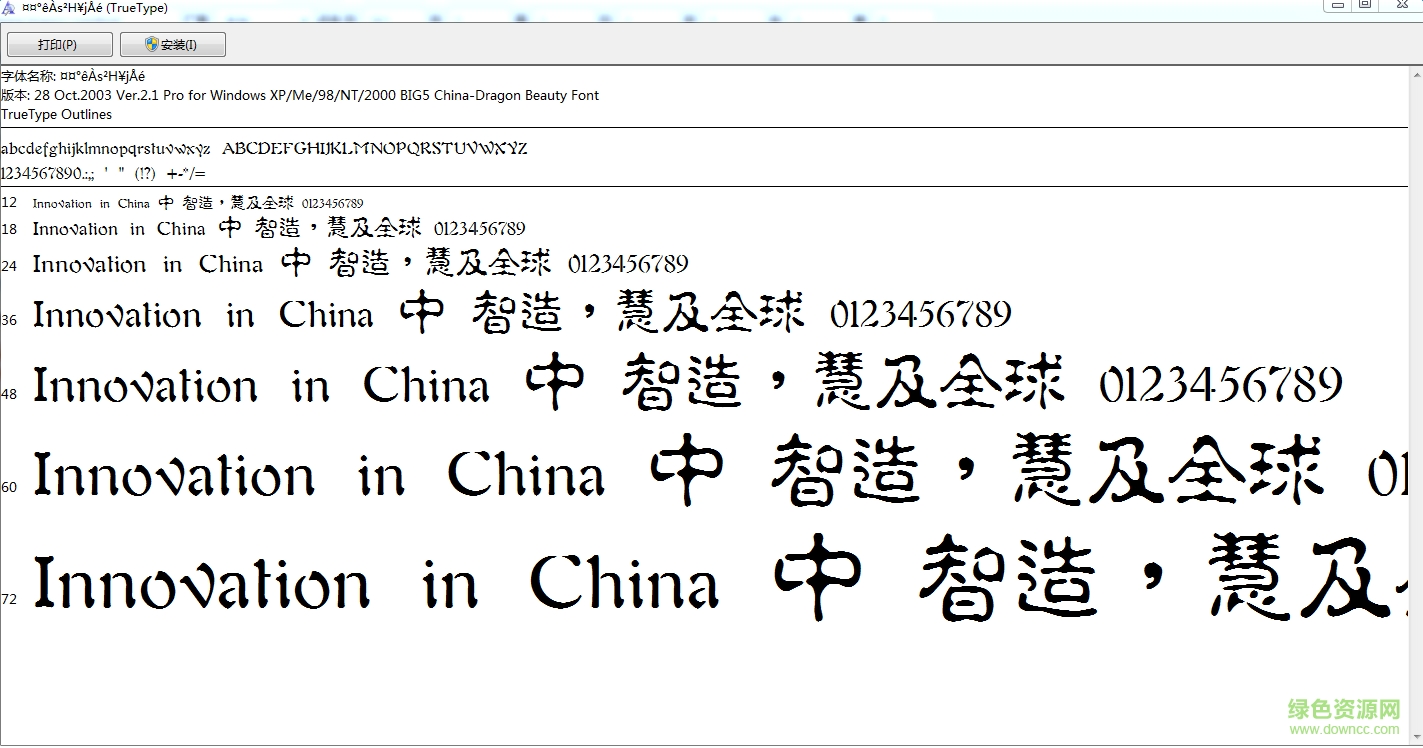
中國龍淡古體簡體
中國龍淡古體是一款典雅的中文古體字體,字體流暢超逸,筆畫飛動,看上去非常漂亮!喜歡的該款字體的朋友快來綠色資源網下載吧!
中國龍淡古體字體介紹
中國龍淡古體是一款用于美工設計方面的字體,整體效果非常統一,且字庫完整,可以廣泛應用于廣告設計、海報、ppt、影視制作以及內容用字等領域,有需要的朋友可以免費下載收藏。
中國龍淡古體樣貌